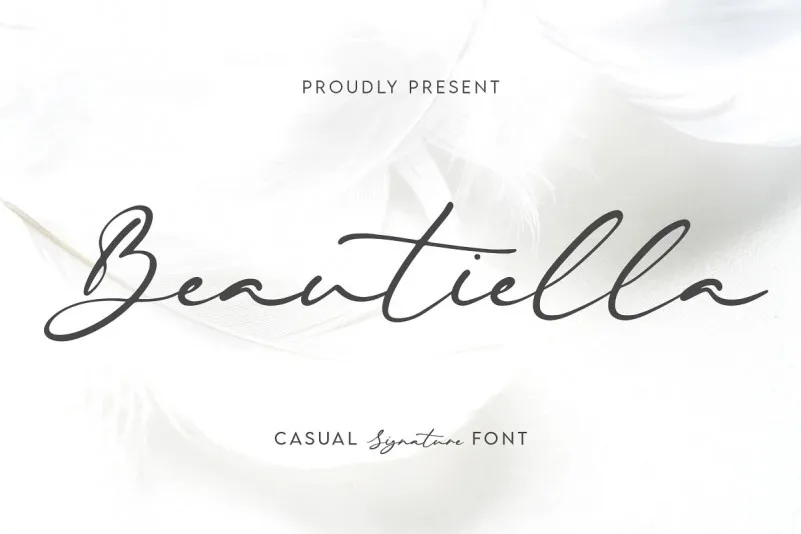
Beautiella Font – Fonte Grátis
Beautiella Font
A fonte ‘Beautiella Font’ traz a elegância e encanto do escrita à mão livre com um efeito de traço rápido. Seu designer adora o charme dessa técnica, que transmite uma sensação de sofisticação. Ela é criada a partir da escrita em papel, após ser rascunhada e retratada meticulosamente num formato vetorial. Se você está procurando por uma fonte suave e elegante para seus projetos, esta pode ser perfeita, seja para cartazes de eventos ou design gráfico online. A ‘Beautiella Font’ oferece um toque autêntico que transmite confiança e sofisticação, tornando-a a escolha ideal para qualquer tipo de projeto visual.